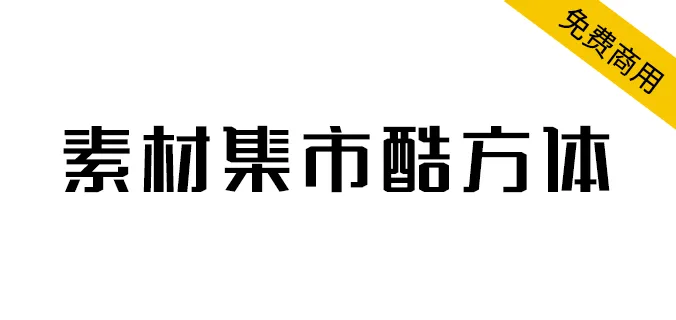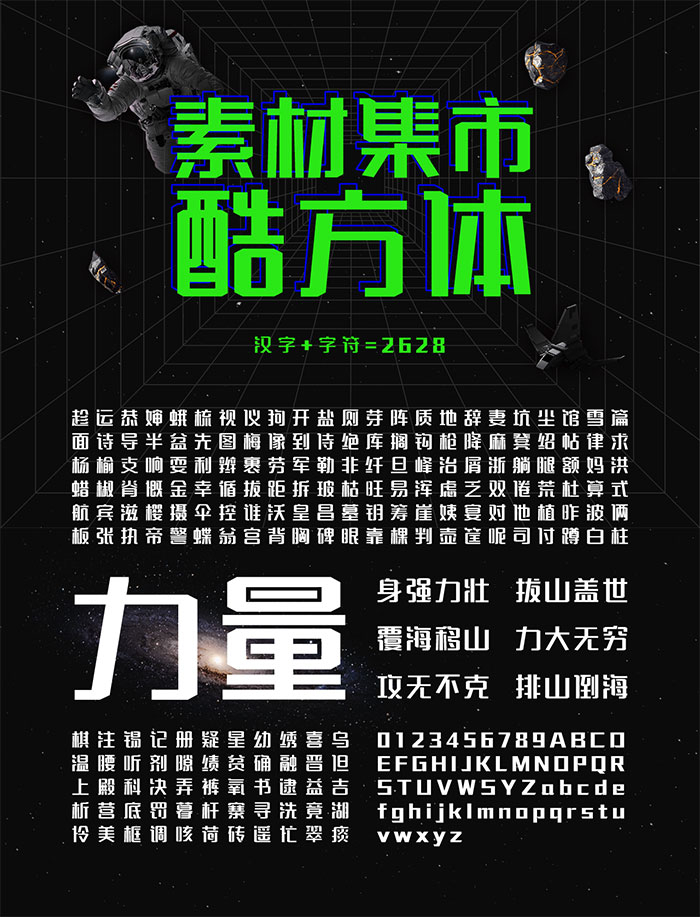
金秋八月是一年收穫的旺季,素材集市發佈今年的原創中文字體「酷方體」,字型方正,筆畫剛勁有力是「酷方體」的特點,由字集團隊的十二名各行業設計師聯合制作完成,感謝成員的辛勤付出和信任。
2020年4月初,素材集市招募十二名各行業現役設計師,組建了字集團隊,“素材集市酷方體”是字集團隊的首款原創字庫。經過幾個月的艱苦奮戰,“素材集市酷方體”已完成了漢字+字符2628個,能基本滿足一般的設計需求。